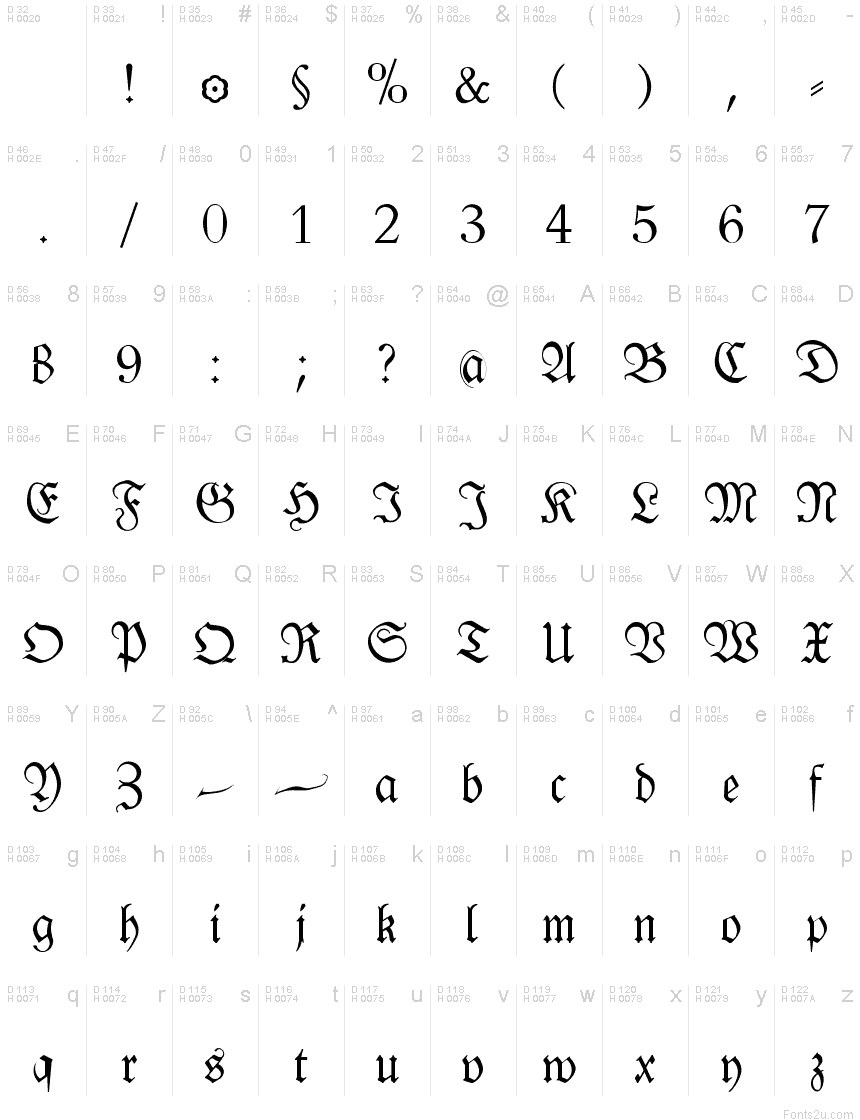
Klaus B Fraktur autorstwa Klausa Burkhardta to darmowy gotycki krój pisma, który nawiązuje do gęstego, „atramentowego” charakteru blackletteru z początków cyfrowych eksperymentów z frakturą. Jego wysokie, wąskie litery, ostre krzywizny i lekko chropowate krawędzie nadają tekstowi ciężar rzeźbionego kamienia i metalowych czcionek, sprawiając, że każde słowo brzmi dostojnie i szlachetnie, nie popadając w nostalgię ani kicz.
nach Klaus Burkhardt einer der ersten Frakturfonts für den Computer, um 1991; ready made M. Klein 10.02